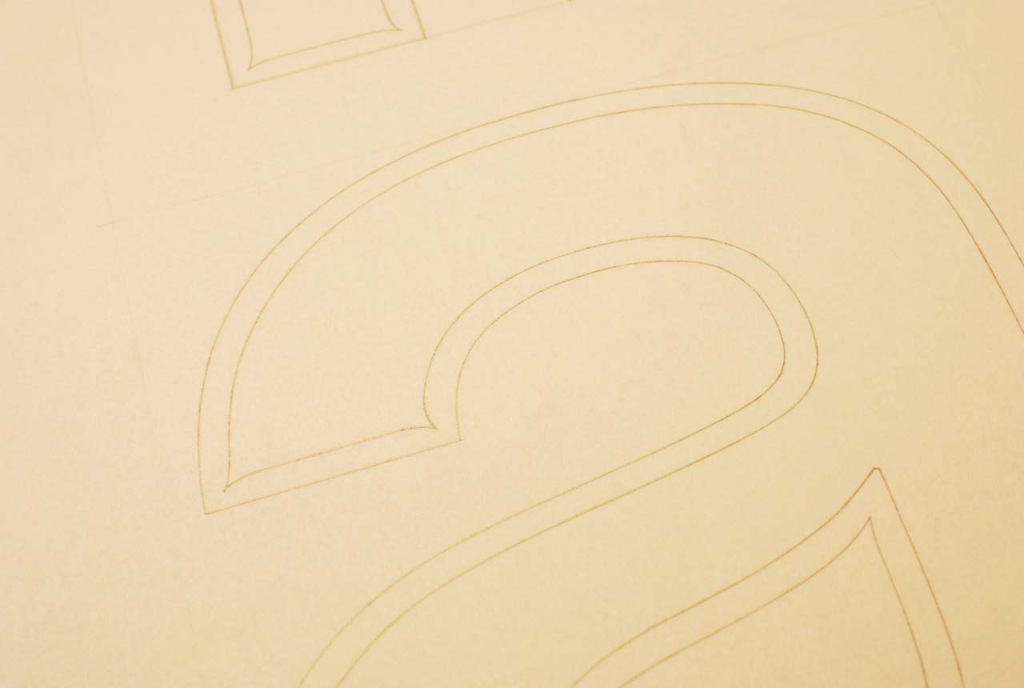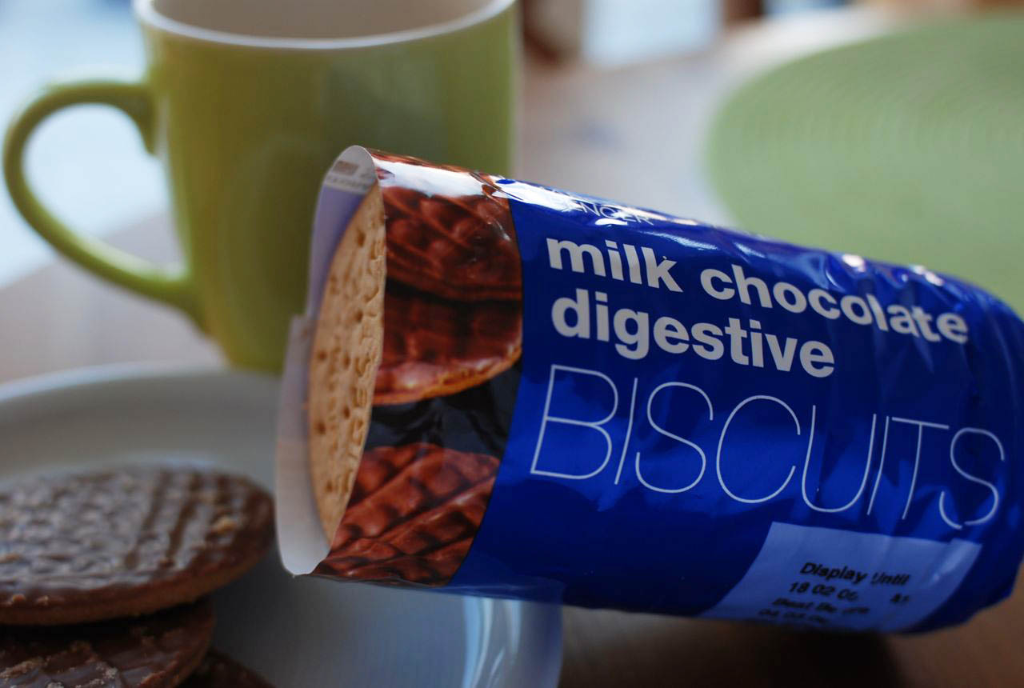
今年年初在大阪和东京同时举办的“Helvetica Forever 展”已落下帷幕。
从莱诺字体公司借出的原图已从日本返回德国。无论看多少次,都会被这些曲线的美丽所折服。绘制这些曲线的工匠真是太厉害了。在会场亲眼看过原图的人,应该能体会到那种震撼吧?为了让没能到会场观看的人也能一睹其风采,稍微给大家展示一下。纸张大小约为 40 厘米见方。
几乎没有直线呢!听说是用云形规绘制的,把这些曲线连接起来可不容易。
要把原图放回原来的盒子里,再送回仓库。
其实,这次在寻找 Helvetica 的原图时,意外发现了一件宝贝(另一种字体的修整记录)。多亏了 Helvetica 展,让我收获了不少乐趣。
从去年开始,我参与了电影《Helvetica》的日语字幕监修、书籍《Helvetica Forever》日语版的监修等工作,协助小泉先生,因此与 Helvetica 有了诸多关联,现在对身边的 Helvetica 也格外留意。最近的趋势是,比较细的字重被大量使用。
这是在德国的车站。以前,在这种地方使用的 Helvetica 字体,粗体应该是很常见的。
这是英国的饼干包装。
这是从德国银行拿到的笔记本。